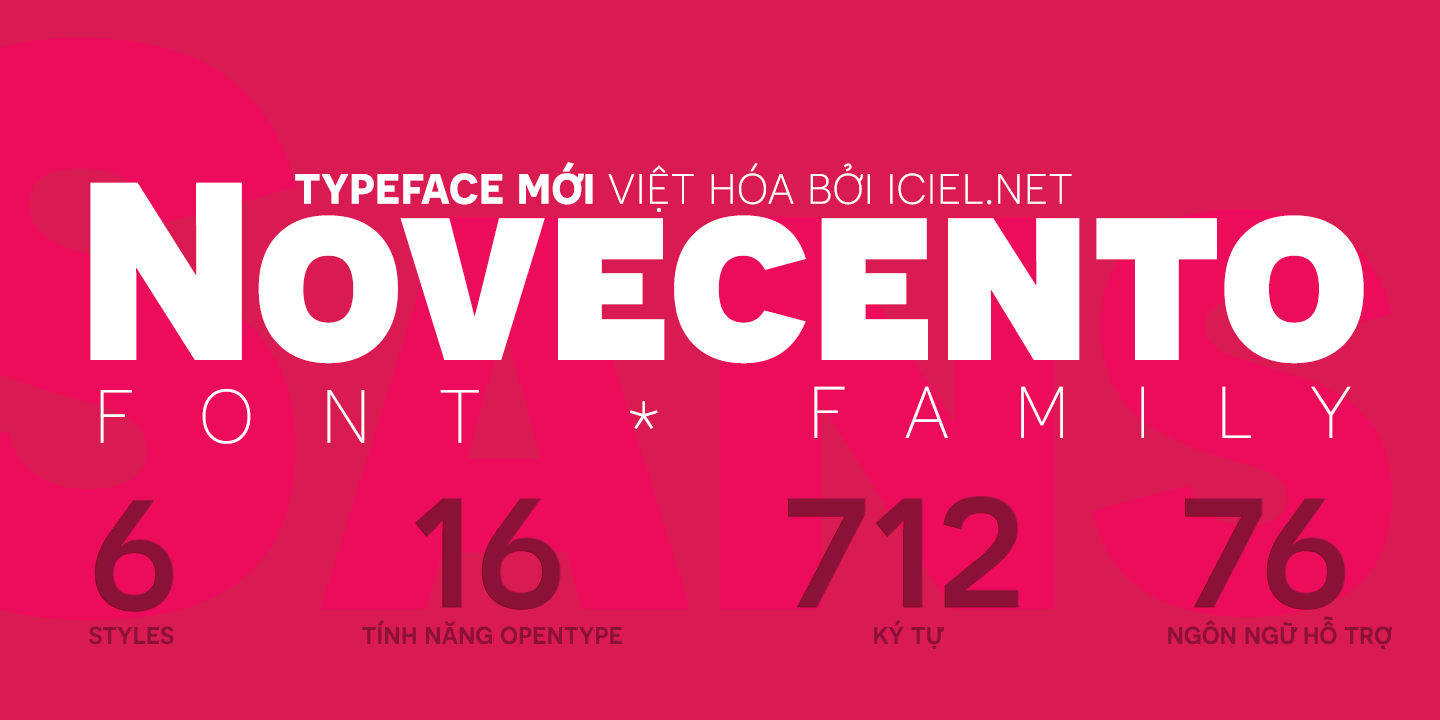
[Sans-serif] Novecento Việt hóa
Thông tin về font Novecento
Hôm nay là một typeface viết hoa được lấy cảm hứng từ xu hướng thiết kế cuối thế kỷ 19 giữa thế kỉ 20. Novecento được thiết kế cho tựa đề, thiết kế thương hiệu hoặc những câu ngắn, cả cỡ to và cỡ nhỏ. Những style mảnh mang không khí hiện đại hơn, trong khi những font đậm trông cổ kính hơn.
Novecento Sans Việt hóa bao gồm 6 style Normal, Ultra light, light, Demi bold và Ultra bold